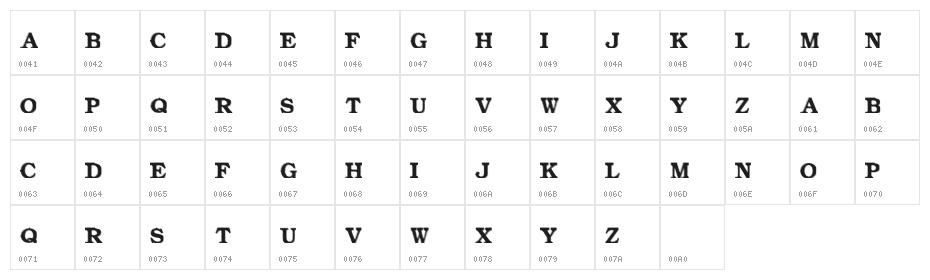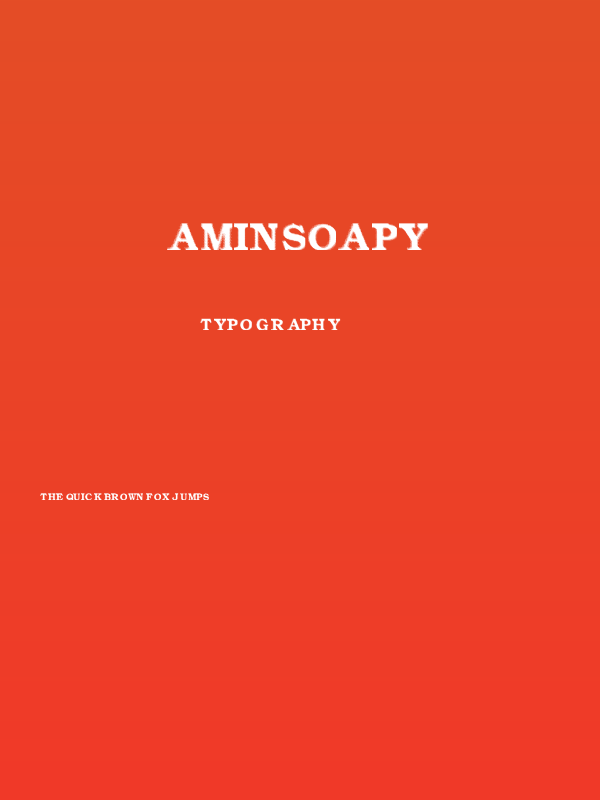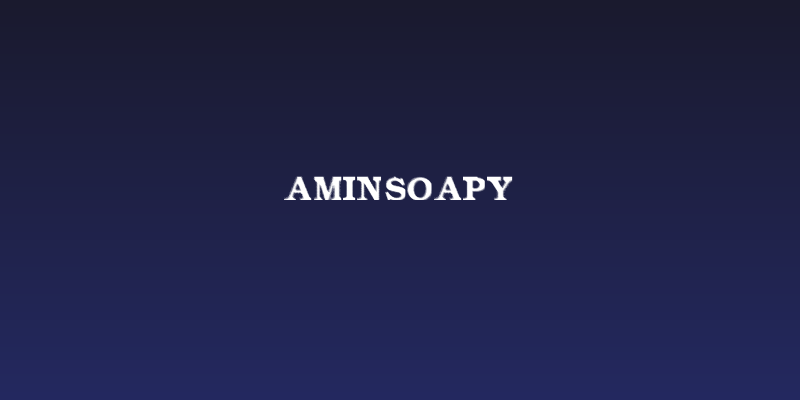
Amin_Soapy Font
| Progetti proposti | Ideal for use in headlines, book covers, posters, and branding materials where a classic and authoritative look is needed. |